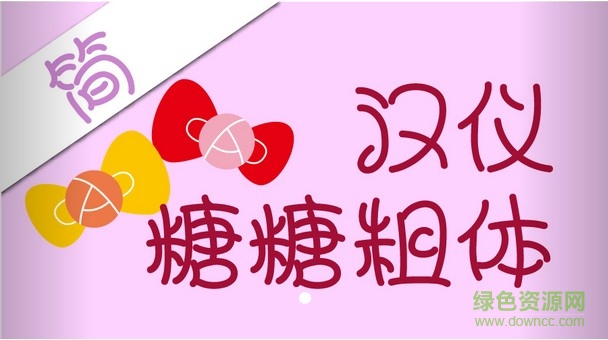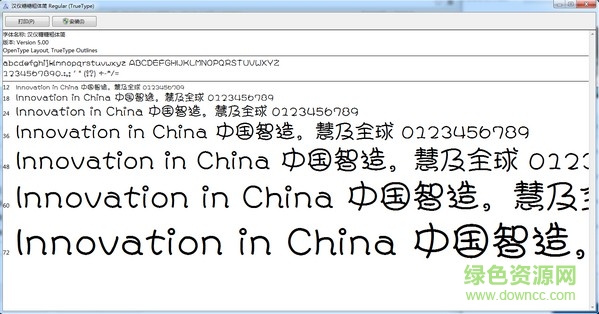
漢儀糖糖粗體簡(jiǎn)
漢儀糖糖粗體簡(jiǎn)是一款卡通風(fēng)格的字體,字體看上去有點(diǎn)棒棒糖的感覺(jué),顯得活潑可愛(ài),富有生氣,主要適用于廣告設(shè)計(jì)、海報(bào)設(shè)計(jì),有需要的快來(lái)綠色資源網(wǎng)下載收藏吧。